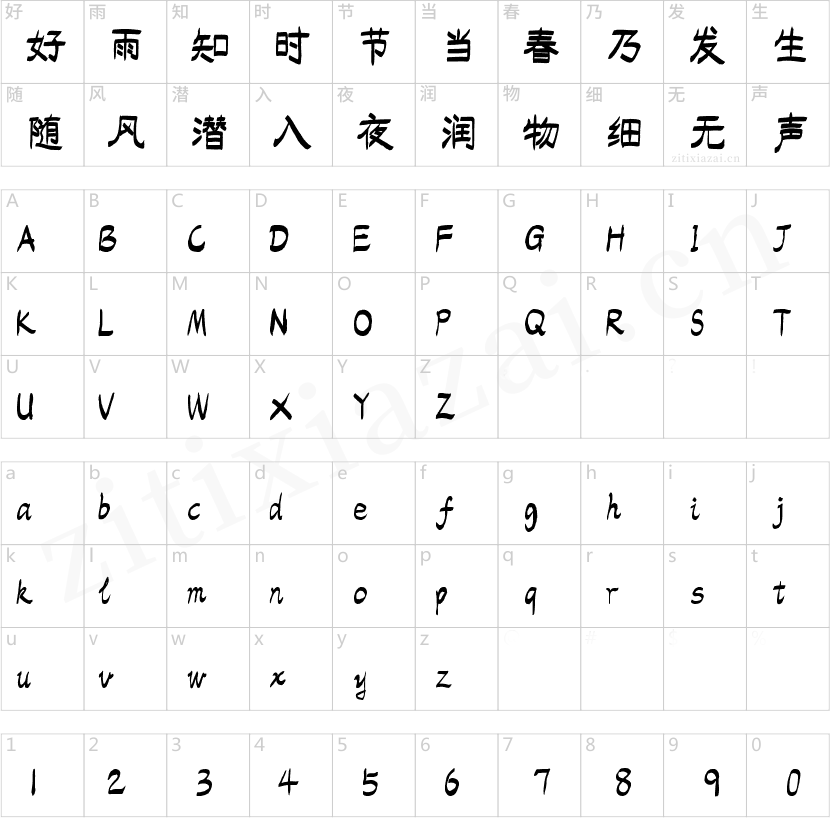
字魂120号-排笔手绘体
字魂120号-排笔手绘体是一款艺术字体,深受广大设计师的喜爱。
字体设计说明
字魂字体字小魂排笔手绘体字体是由字魂创意字库设计并生产的一款可商用的字体,被收录于字小魂系列。该字体支持GB-2312标准,包含6764个中文、字母、符号和数字,字体类型偏向硬笔手写,具有力量、简约、时尚的风格,在市面上广泛用于企业文化、排版阅读、房地产等场景。